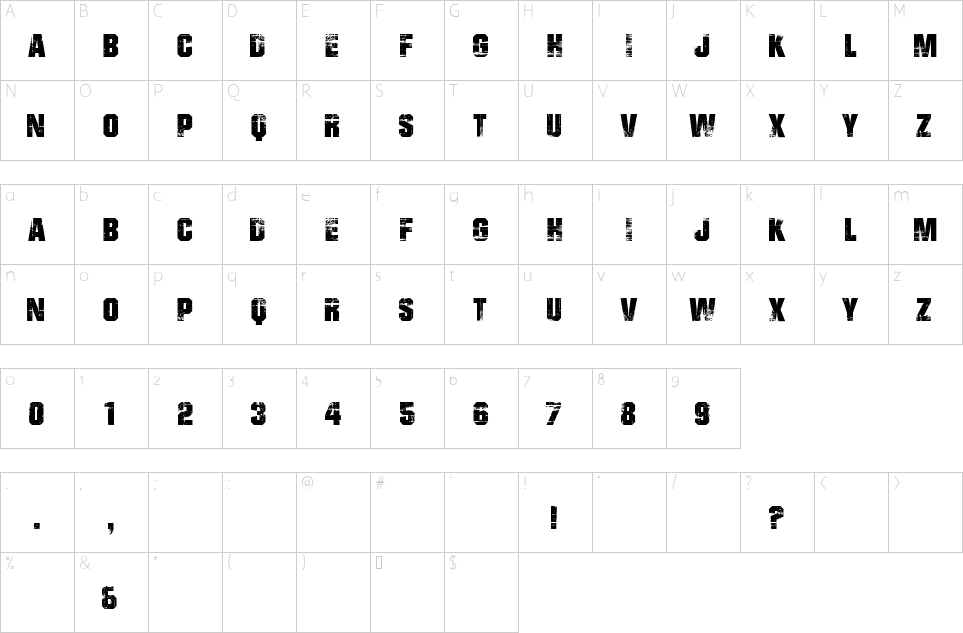
Descubra a Bad Grunge Font, uma elegante e única opção para designers que buscam adicionar um toque distinto a suas criações digitais. Desenvolvida pelo designer Jayde Garrow, esta font se destaca pela sua graça antiga e personalidade brusca, criando um contraste vibrante e interessante em qualquer projeto. Se você está procurando por uma fonte que possa dar vida a seus designs de maneira única e moderna, a Bad Grunge Font pode ser perfeitamente o que você precisa. Com sua arquitetura gráfica impecável e personalidade inovadora, esta font é um dos recursos mais populares na categoria de fonts gratuitas. Para usuários de Windows ou Mac, temos grande satisfação em oferecer a Bad Grunge Font para download gratuito. Essa font não apenas adicionará uma cara nova ao seu design, mas também o tornará ainda mais relevante e chamativo. Acesse nosso site agora e descubra por si mesmo como essa font pode transformar sua experiência de criação digital.